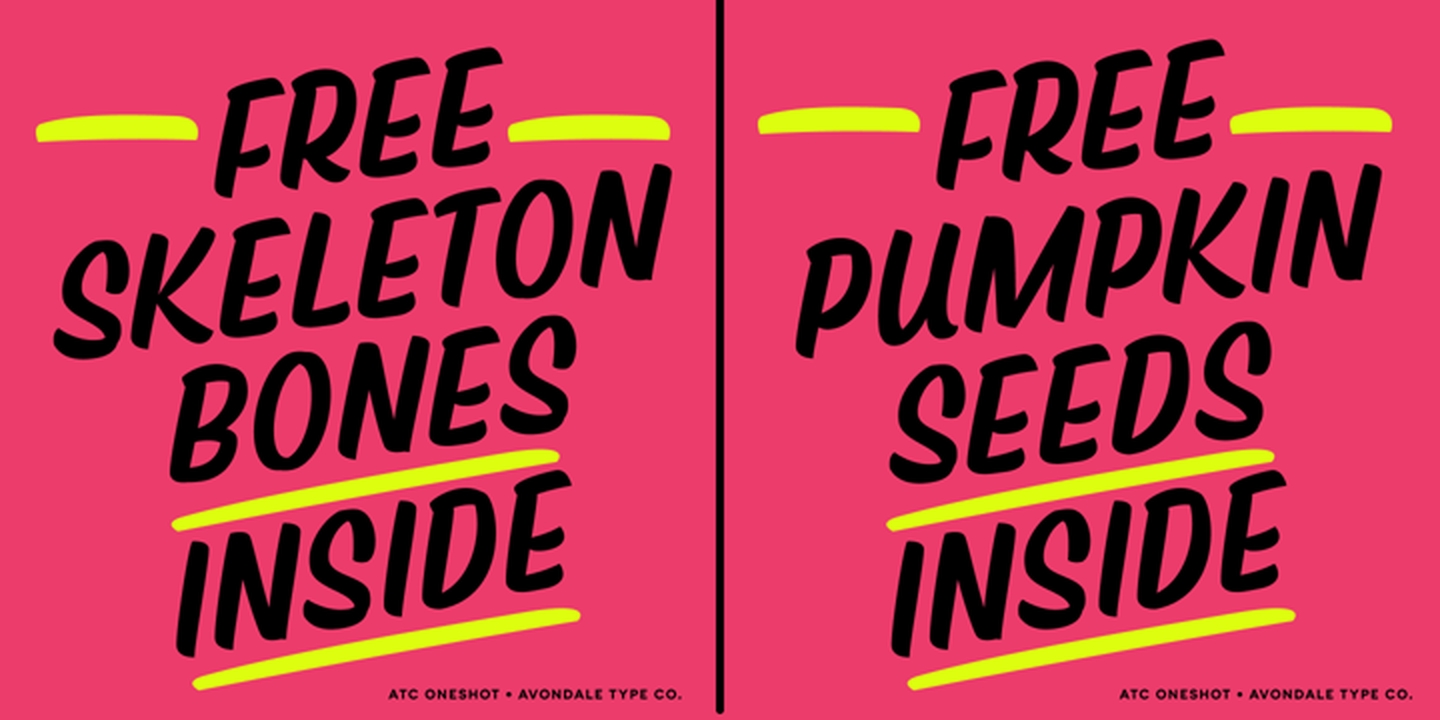
ATC Oneshot Font Family
ATC Oneshot est une police de script manuscrite basée sur la signalisation des bodegas du quartier. Contient plus de 160 glyphes, alphabet complet, ligatures, chiffres, accents et ponctuations. Le type de fichier inclus dans le téléchargement est .otf.